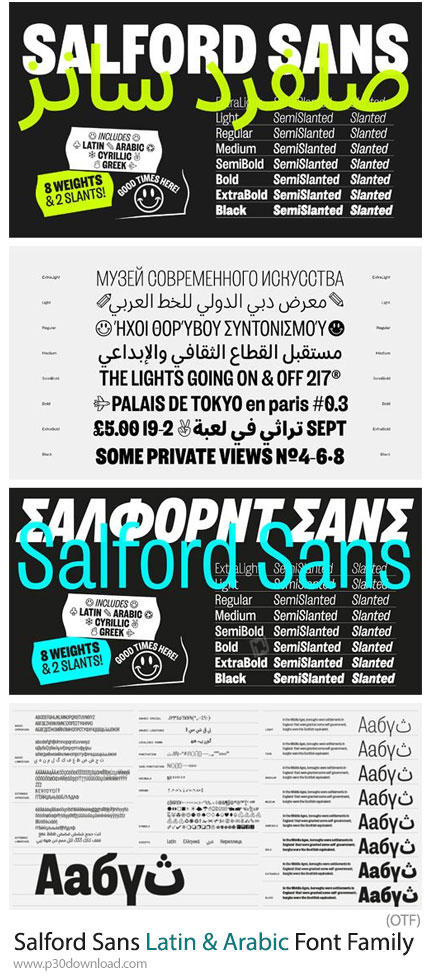
در این بخش شاهد فونت لاتین و عربی صلفرد سانز می باشید که با فرمت OTF بر روی سایت برای دانلود قرار گرفته است. فونت Salford Sans Latin & Arabic Font Family یک خانوادهی تایپوگرافی مدرن و همهکاره است که بهطور حرفهای برای پوشش زبانهای لاتین و عربی طراحی شده است. این خانواده فونت برای طراحانی ساخته شده که به دنبال هماهنگی کامل میان متون انگلیسی و عربی در پروژههای چندزبانه هستند. سبکهای لاتین و عربی در این خانواده فونت بهصورت کاملاً هماهنگ طراحی شدهاند تا انسجام بصری در پروژههای چندزبانه ایجاد کنند. این فونت با تمرکز بر خوانایی و سادگی، مناسب برای استفاده در وبسایتها، اپلیکیشنها، تبلیغات، نشریات، و طراحی برندینگ است. طراحی بر پایهی اشکال هندسی نرم و متوازن انجام شده که حس مدرن، مینیمال و حرفهای به پروژهها میدهد.